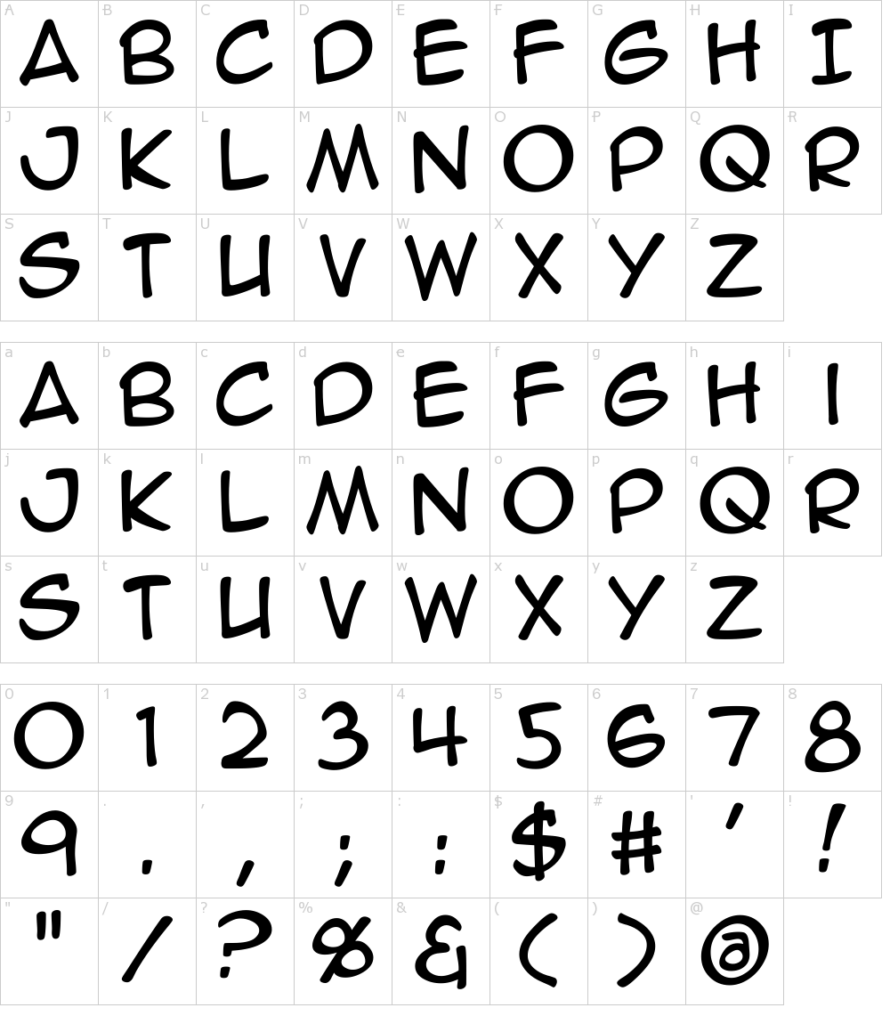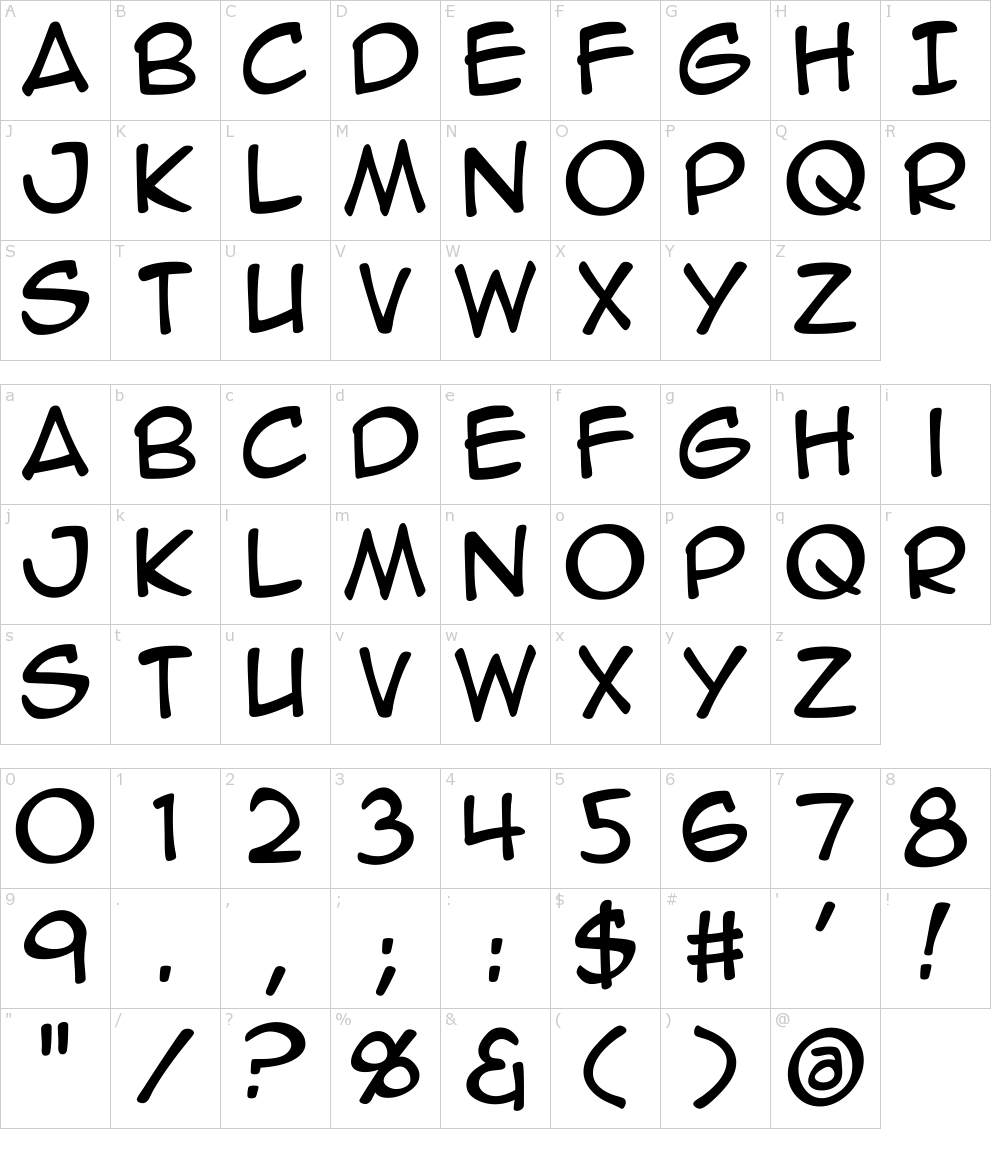
En el entorno del diseño digital, la búsqueda de la fuente perfecta puede ser un desafío. Si eres un entusiasta del anime o simplemente buscas un estilo único y llamativo, el concepto de un generador de fuentes Anime Ace puede resultar muy atractivo. Aunque no existe un generador específico con ese nombre, podemos explorar las opciones disponibles para crear fuentes con ese estilo.
¿Qué son las fuentes Ace?
Antes de adentrarnos en el entorno del anime, entendamos qué son las fuentes Ace. En el contexto del bordado digital, las fuentes Ace se refieren a un tipo de fuente específicamente diseñada para el warping (deformación) dentro de formas o sobres predefinidos. Estas fuentes, por lo general, son mayúsculas y están diseñadas sin ascendentes ni descendentes para integrarse perfectamente en las formas, garantizando una apariencia limpia y profesional.
Las fuentes Ace ofrecen una gran versatilidad y se utilizan en software de diseño como Embrilliance. Se caracterizan por:
- Mayúsculas: Diseñadas sin ascendentes ni descendentes.
- Integración perfecta con formas: Adaptan su forma para ajustarse a sobres predefinidos.
- Control total: Permiten un control preciso sobre el espaciado y la adaptación al diseño.
- Amplia gama de estilos: Ofrecen una variedad de estilos para adaptarse a diferentes proyectos.
Creando Fuentes con Estilo Anime
Si bien no hay un generador de fuentes Anime Ace como tal, podemos lograr un estilo similar utilizando diferentes herramientas y técnicas. Aquí te presentamos algunas opciones:
Fuentes Prediseñadas
Editores de Fuentes
Para un control más preciso, puedes utilizar editores de fuentes como FontForge (gratuito y de código abierto) o Glyphs (de pago). Estos programas te permiten diseñar y modificar fuentes desde cero, permitiéndote crear tu propia fuente con estilo anime, con la posibilidad de integrar las características de las fuentes Ace.
Generadores de Texto con Estilos
Algunos sitios web ofrecen generadores de texto con estilos predefinidos. Aunque no crean fuentes propiamente dichas, te permiten generar texto con apariencia anime para su uso inmediato en tus proyectos. No ofrecen la misma flexibilidad que los editores de fuentes, pero son una opción rápida y sencilla.
Comparativa de Opciones
| Método | Flexibilidad | Coste | Tiempo |
|---|---|---|---|
| Fuentes Prediseñadas | Baja | Gratis/Pago | Bajo |
| Editores de Fuentes | Alta | Gratis/Pago | Alto |
| Generadores de Texto | Media | Gratis | Bajo |
Consultas Habituales
- ¿Puedo crear mi propia fuente anime? Sí, utilizando editores de fuentes como FontForge o Glyphs.
- ¿Qué diferencia hay entre una fuente Ace y una fuente anime? Las fuentes Ace son un tipo de fuente optimizada para el warping en bordado digital, mientras que las fuentes anime se refieren a un estilo estético.
- ¿Hay un generador de fuentes que combine ambos estilos? No existe un generador específico, pero puedes combinar fuentes prediseñadas con los editores de fuentes para lograr el efecto deseado.
Consejos Adicionales
Recuerda que al buscar fuentes anime, puedes encontrar una amplia variedad de estilos. Algunos son más cercanos a la caligrafía japonesa tradicional, mientras que otros optan por una estética más moderna y estilizada. Experimenta con diferentes opciones hasta encontrar la que mejor se adapte a tu proyecto.
Si decides utilizar editores de fuentes, ten paciencia y dedica tiempo al proceso de aprendizaje. Crear una fuente desde cero requiere práctica y dedicación. Puedes encontrar tutoriales en línea para aprender a usar los programas de edición de fuentes.
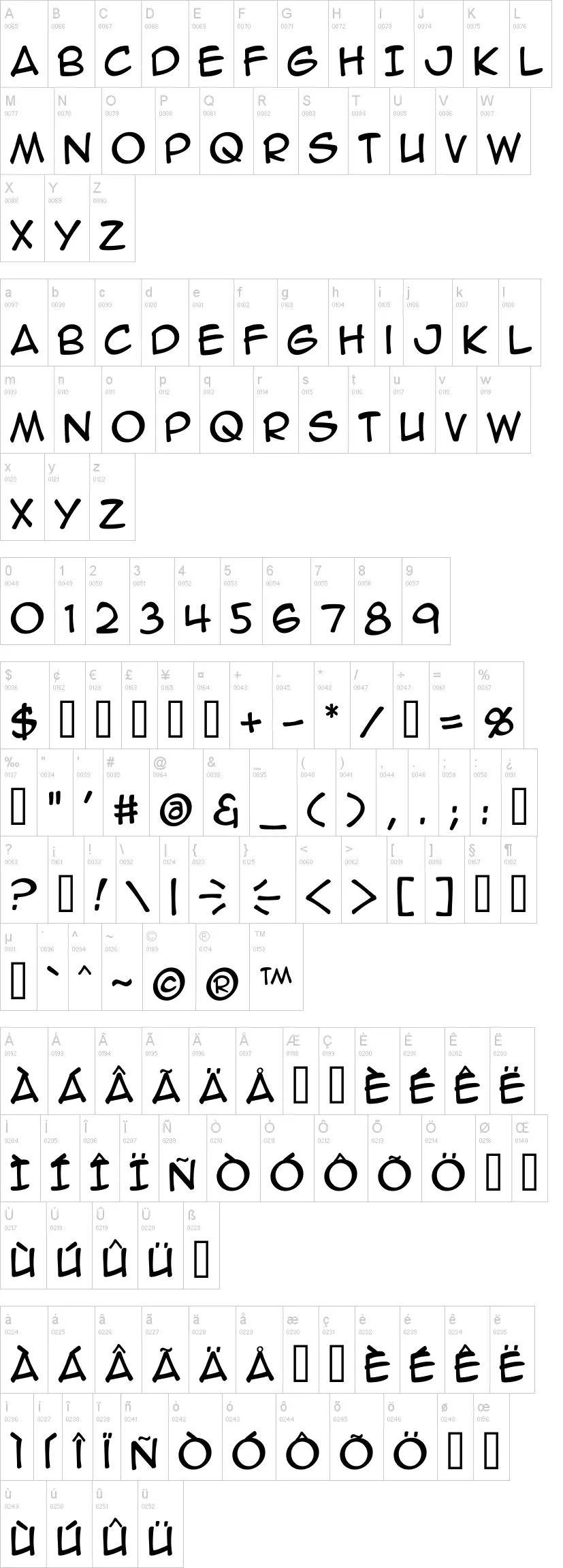
Aunque un generador de fuentes Anime Ace no existe actualmente, existen numerosas opciones para crear texto con estética anime. La elección del método dependerá de tu nivel de experiencia, tu presupuesto y el nivel de personalización que necesites.